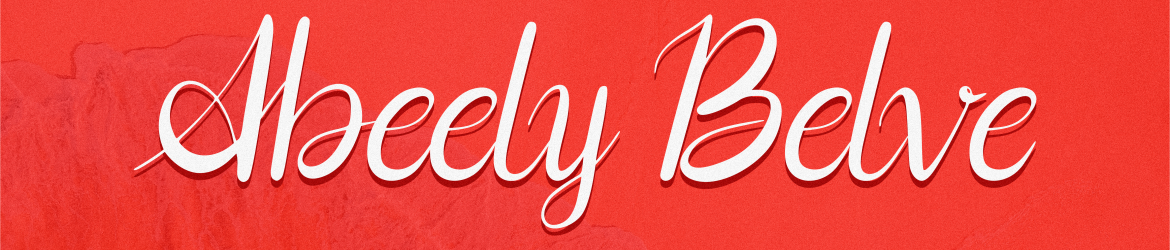
Abeely Belve Font – Fonte Grátis
Abeely Belve Font
Abeely Belve é uma elegante fonte escrita à mão perfeita para qualquer projeto visual que deseje destacar a autenticidade e delicadeza do texto sobre qualquer fundo. Conhecida por sua natureza fluida e bem definida, Abeely Belve combina os elementos essenciais de uma fonte criada pelo homem com o encanto dos traços naturais da escrita à mão, tornando-a perfeitamente adequada para diversas aplicações. Essencialmente perfeita para uso em pacotes de produto, criação de marcas, revistas, mídias sociais e até mesmo para expressar frases no topo de uma página com fundo. Adicionalmente, a fonte possui um charme especial que permite sua utilização versátil. É especialmente indicada para projetos como embalagens de produtos, onde o texto transmite uma sensação única e autêntica. Para empresas criando marcas memoráveis, Abeely Belve traz um toque único capaz de destacar a personalidade da marca. Se você está pensando em criar uma revista que transmita um sentimento pessoal ou para qualquer aplicativo que utilize mídias sociais, Abeely Belve tem o poder de transformá-lo, dando-lhe aquele toque especial que faz com que sua publicação seja lembrada. Não importa qual seja seu próximo projeto. Abeely Belve é uma fonte apropriada e fácil de usar que trará um encanto único para suas produções. Com sua facilidade de uso em textos expressivos ou simples, ela é uma escolha ótima para designers buscando manter o estilo pessoal em suas criações.